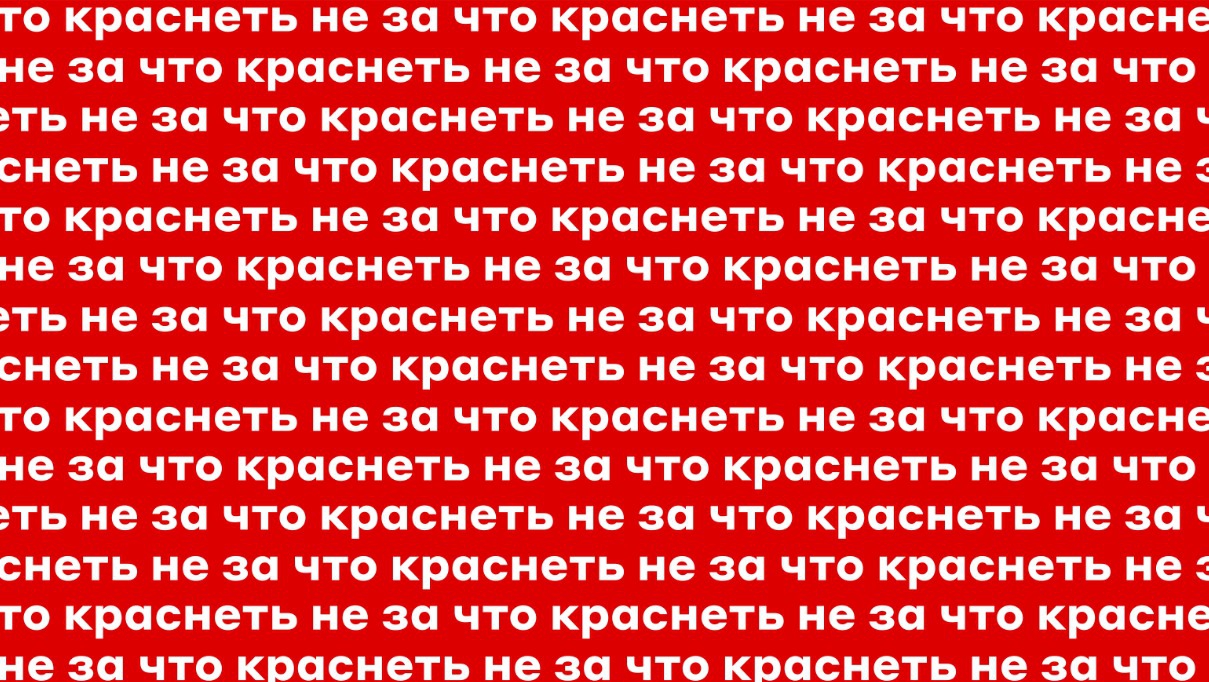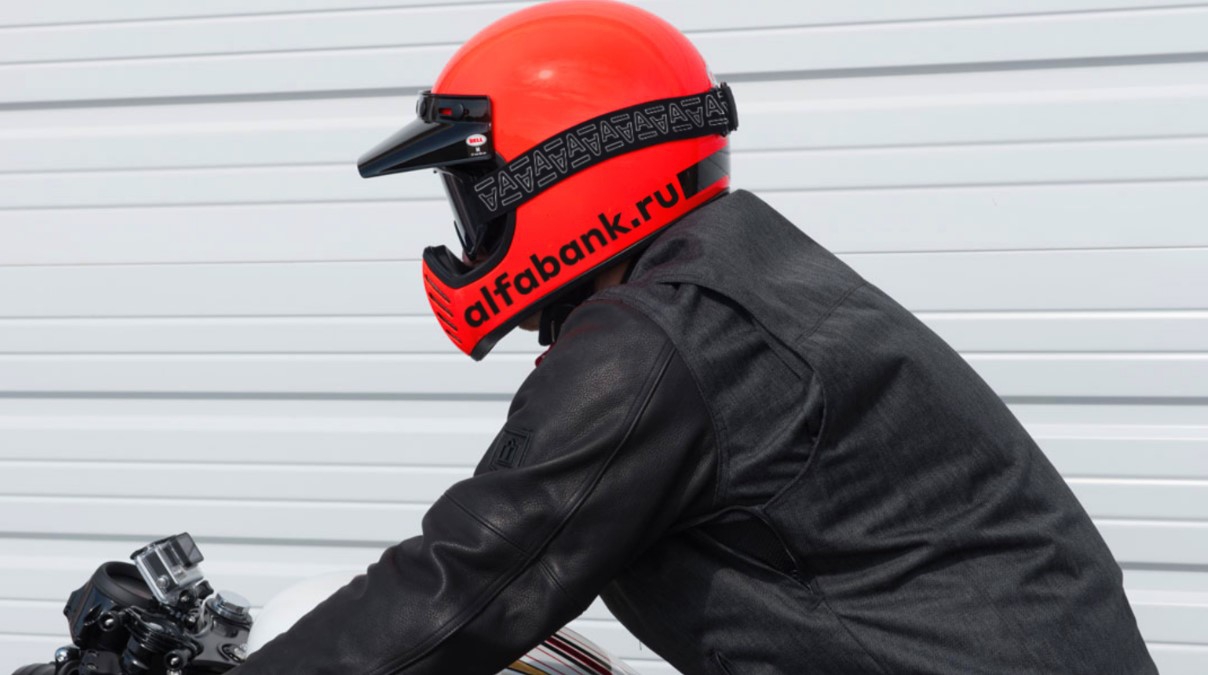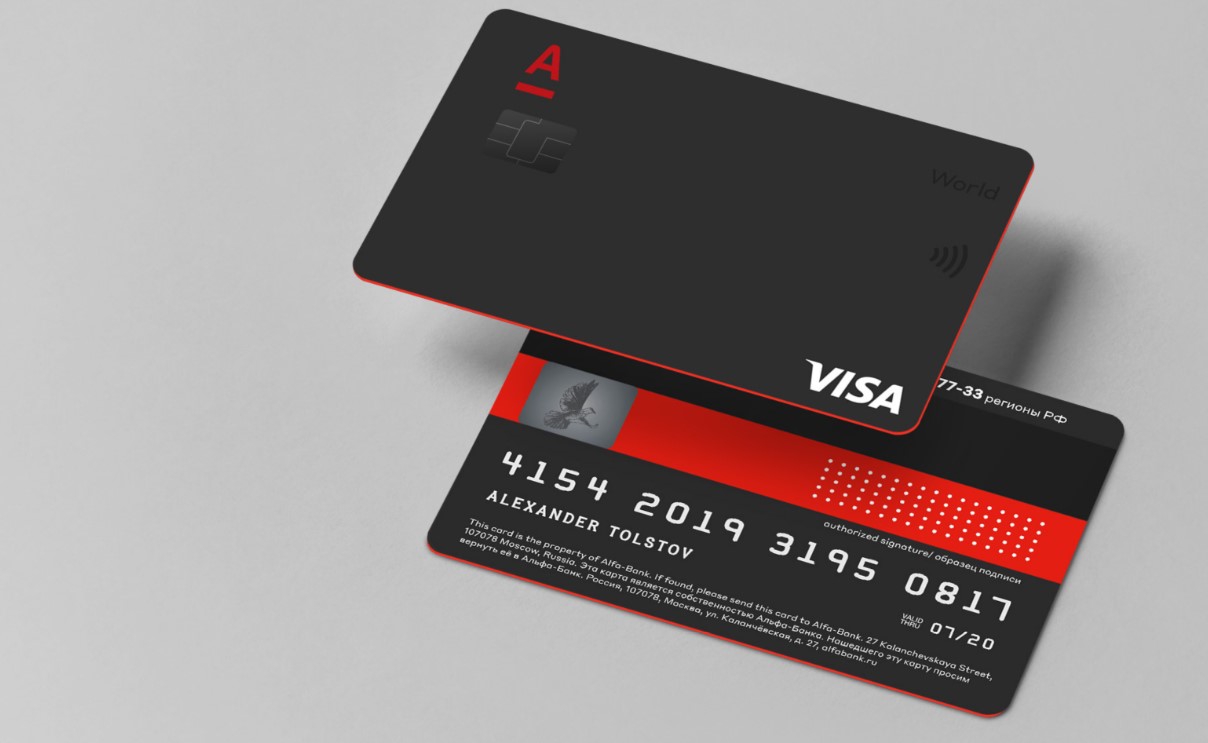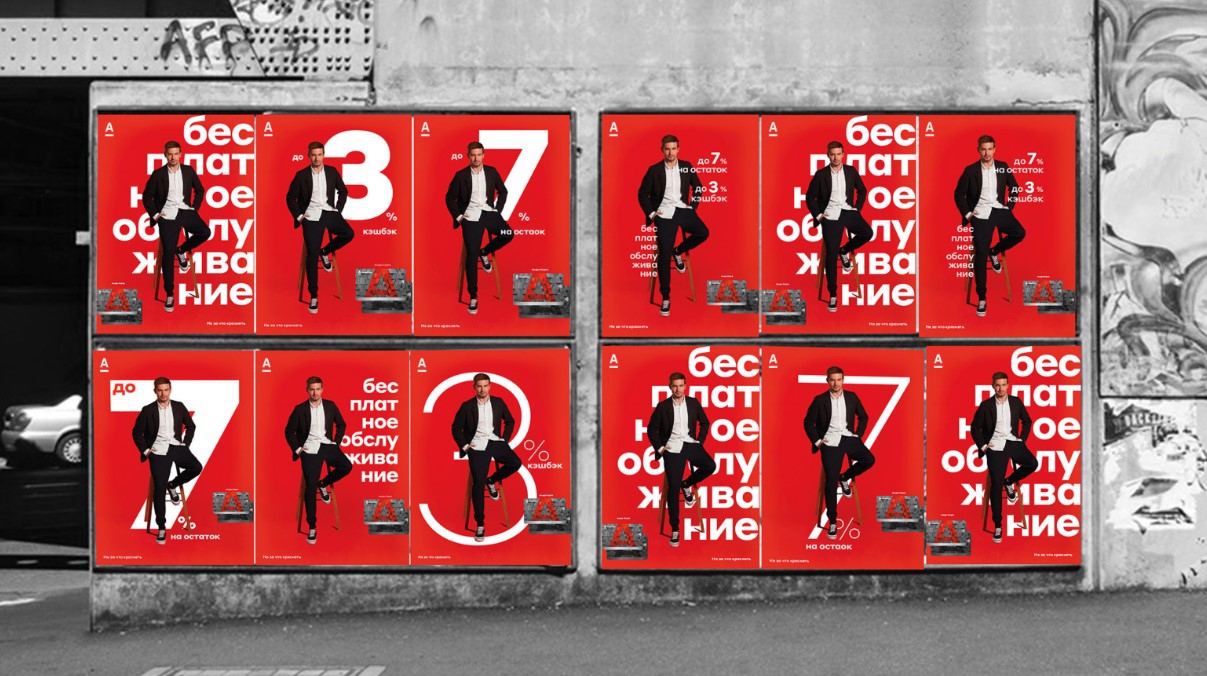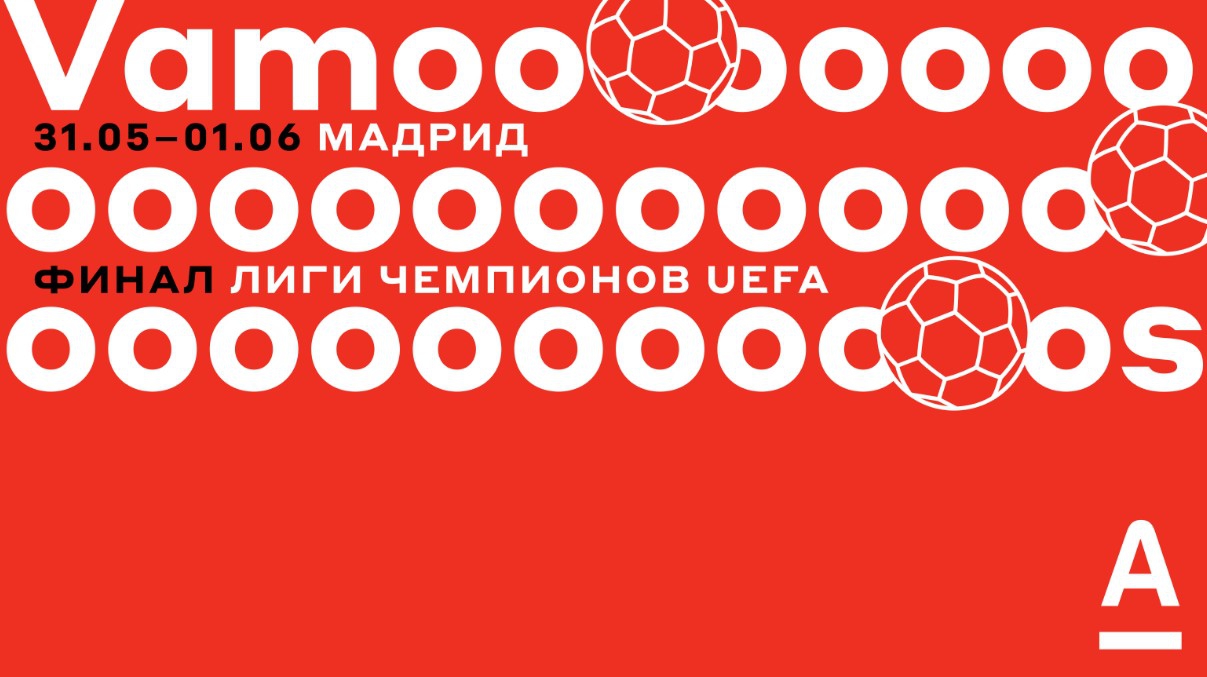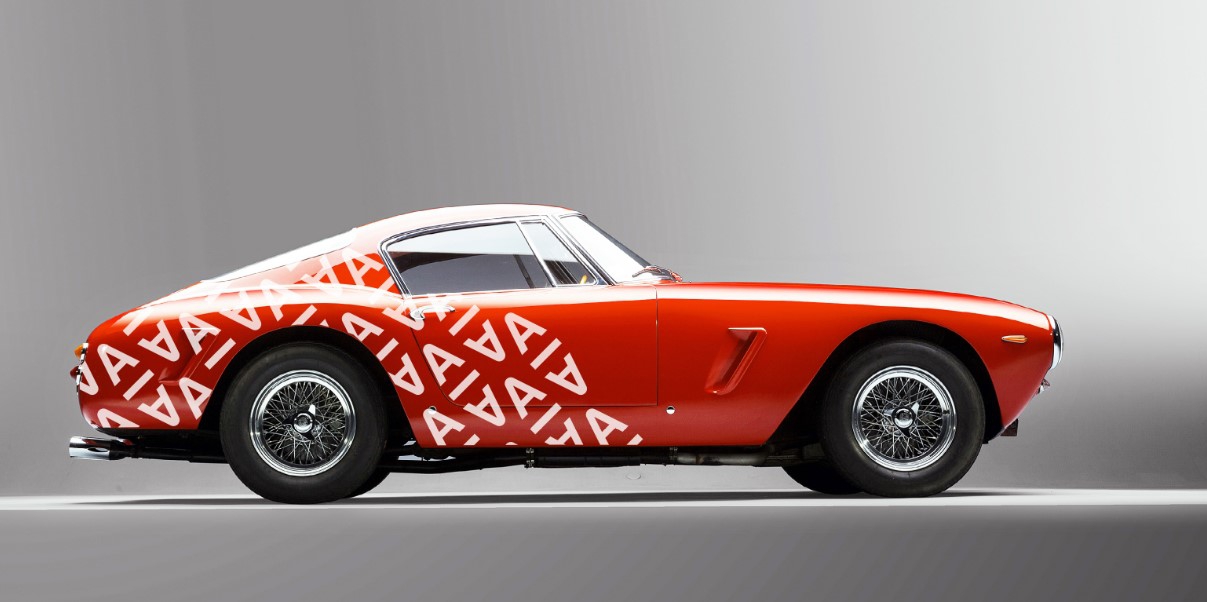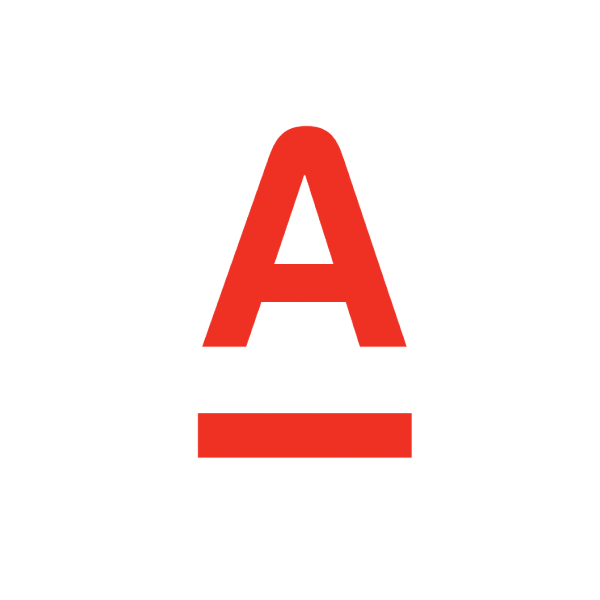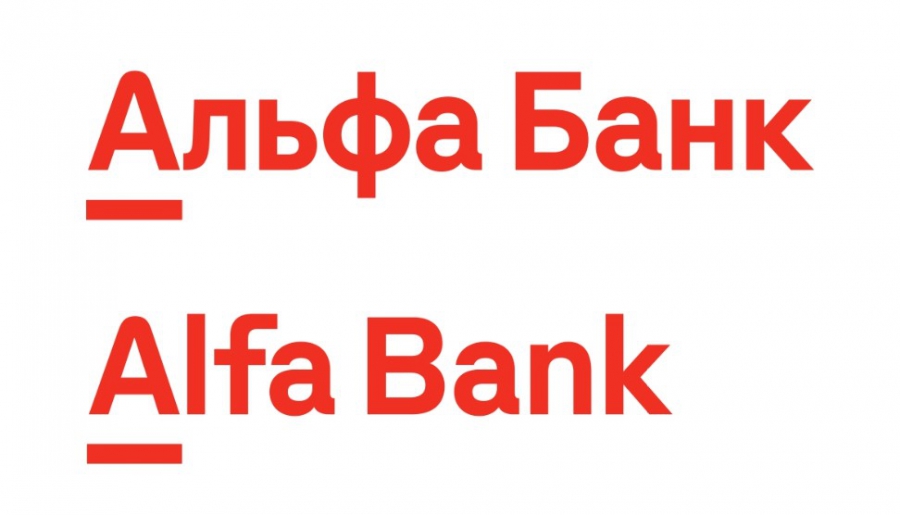
В рамках обновления айдентики «Альфа-Банк» представил логотип, основанный на шрифте Styrene A. Изменен как основной логотип, представляющий собой подчеркнутую литеру А, так и дополнительный, с названием банка.
Основная версия логотипа — обновленная литера А. Знак приобрел устойчивость, а углы фундамента и ножки литеры избавились от скруглений. Теперь логотип корректно растрируется при использовании в цифровой среде. Пластика литеры основана на графике фирменного шрифта, вместе они строят узнаваемую архитектуру бренда.
В дополнительной версии логотипа на смену сложной и избыточной конструкции «А Альфа-Банк» пришел облегченный вариант, где литера «А» интегрирована в полное название.
Новая айдентика позволит выстроить единую архитектуру бренда с продуктовым брендингом и саббрендами. При этом речь идет не о ребрендинге, а именно об обновлении. Прошлая версия лого была разработана под физические носители, обновленный логотип и шрифт гораздо лучше работают в цифровой среде.
Обновленная айдентика является внутренней разработкой «Альфа-Банка». Консультантами выступили Илья Рудерман, Юрий Остроменцкий и шрифтовой магазин type.today.
Мне очень нравилось прошлое изменение фирменного стиля «Альфа-Банка», когда WollfsOllins представили концепт с подчеркнутой А. Однако шрифтовая часть давно требовала обновления. Мы помогли обновить логотип, сделав шрифтовую часть плотнее и иначе ее сбалансировав. Я рад, что удалось, с одной стороны, сохранить завоевания предыдущего стиля, а с другой, вывести айдентику на современный уровень.
Замена логотипа будет происходить постепенно по мере ротации маркетинговых материалов. Новые офисы «Альфа-Банка» будут открываться в обновленной айдентике, вывески на действующих отделениях будут меняться в рамках планового ремонта. Во всех маркетинговых коммуникациях банка будет использоваться шрифт Styrene A.